Roboto是什么?全面解答
字体是设计中的核心元素,有着重要的作用,他可以传达信息,使用户更加容易接受和理解产品、可以美化整体设计,让设计更加美观大方,是一种看得见的美。Roboto是什么?Roboto 是一个拥有丰富字体资源的网站,它涵盖的字体种类丰富,适用于多种场景,可以帮助我们快速的进行字体设计,寻找设计字体的灵感,是一个非常好用的字体资源库。Roboto 中提供了大量免费的字体资源,都可免费使用。接下来就让我们一起来看看 Roboto字体库的详细介绍吧!
1、Roboto是什么?
Roboto 是一个拥有丰富字体资源的网站,它里面提供了 135 种语言的字体,有 1500 + 的免费字体资源。涵盖的字体种类丰富,适用场景多样,有手写的字体,也有印刷的字体,字体筛选的条件分类也很齐全。除了选择既有字体使用以外,Roboto 也支持用户定制字体,创建字体集,可以对字体颜色、大小、粗细等进行更改,可以帮助快速高效的进行字体设计,是一个很好用的字体资源库。
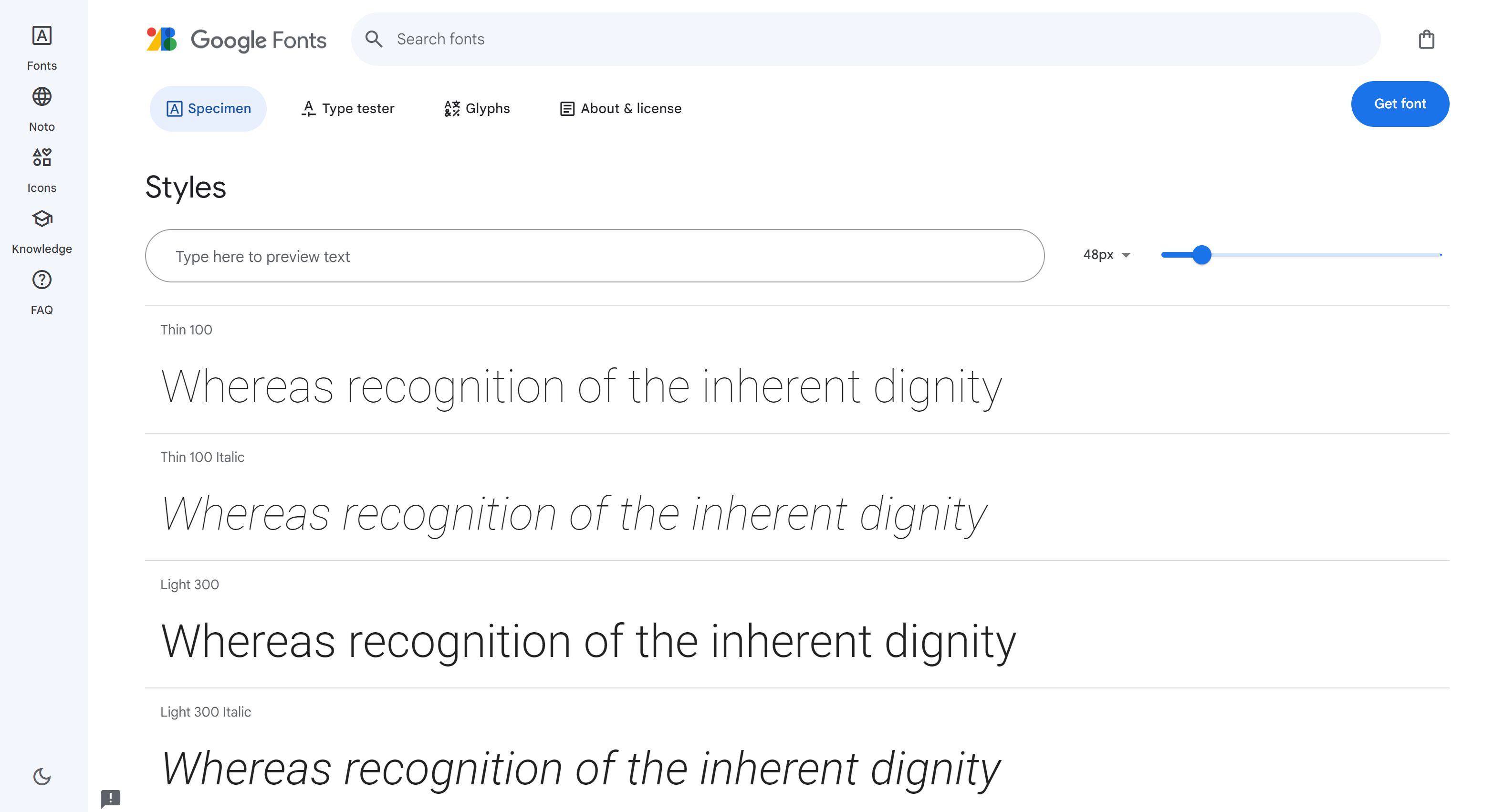
Roboto 字体简洁、清晰和易读,广泛应用于互联网和各种移动应用中,包括网页设计、移动应用界面、品牌标识等。还适用于各种风格的设计,从现代化的科技感到简约的平面设计都能得到很好的展示效果。并且在不同尺寸和屏幕上都能保持良好的可读性。